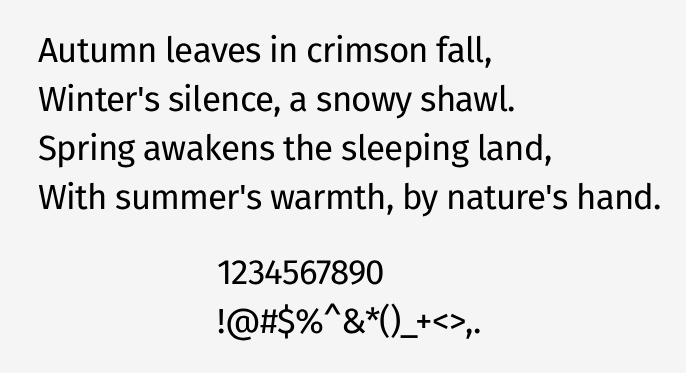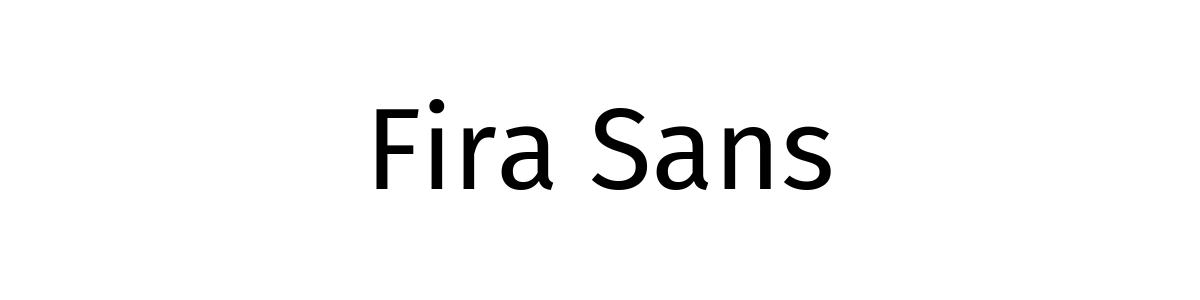
Fira 2026年4月3日 上午11:12 • 英文字体 • 阅读 256 目录 字体预览字体风格字体下载 Fira 是 Mozilla 推出的一套现代无衬线字体,最早为 Firefox OS 设计,专门适配小屏幕和界面显示。名字在瑞典语里是 “火” 的意思,风格也如其名,清晰锐利、很有活力。 它支持拉丁、希腊、西里尔等多种文字,字重选择丰富,还支持连字、小型大写等排版功能。 字体预览 Fira 选择预设预览文本 选择预设文字 Hello, World 1234567890 !@#$%^&*()_+,. A- A+ 自定义预览文本 选择字体字重 Light Regular Bold 字体风格 Fira 字体字形开阔、比例匀称,字符高度适中,小屏幕上看也很清楚。笔画简洁干脆,整体偏理性、有科技感,用来做界面、代码和正文都很合适。 字体下载 Fira 下载次数 11 字体类型 无衬线 授权协议 OFL 授权类型 免费商用 刷新 OFL无衬线英文阅读字体 赞 (0) 0 0 生成海报 相关推荐 英文字体 G8321 G8321 是一款支持免费商用的开源字体,一共包含 9 种字重,同时还提供了可变字体版本。主打现代感与实用功能,字形轮廓清晰利落,笔画扎实稳重。搭配可变字体特性,只用一个字体文件,就能实现从纤细精致到厚重有力的风格切换,适配不同排版场景的需求。 2026年4月1日 2550 英文字体 Source Serif 是 Adobe 在 2014 年推出的一款开源衬线字体,由知名设计师 Frank Grießhammer 完成主设计。它属于 Adobe Source 字体家族,不仅是思源宋体中西文部分的原型,自身也是一套完整成熟、广受好评的独立字体。 2026年3月27日 4060 英文字体 Raleway 是一款从单一字重逐步发展成熟的无衬线字体。最初由 Matt McInerney 设计,只有一款细体,多用于标题展示。后来经过多位设计师扩充,在 2012 年形成了从 Thin 到 Black 共 9 个字重的完整字体家族,并由 Igino Marini 完成字距微调。2013 年加入了标准斜体,近年又推出可变字体,排版更加灵活。 2026年4月4日 4450 英文字体 Roboto Serif 由 Google 委托知名字体公司 Commercial Type 设计,并非对 Roboto 的简单衬线化,而是从零开始构建的全新作品。其核心设计理念是为屏幕和印刷环境提供良好的阅读体验,并与 Roboto 无衬线字体在视觉节奏和家族体系上的和谐搭配。 2025年12月29日 2950 英文字体 Help Me 是一款模拟在粗糙表面(如混凝土或木质)上划伤痕迹的免费英文字体,以其原始、粗粝的手工质感为特征。其设计核心在于完全模仿手工划刻的视觉效果,包含了英文大小写字母、数字及基本标点符号在内的 104 个字形。 2026年1月11日 2900 发表回复 请登录后评论...登录后才能评论 提交